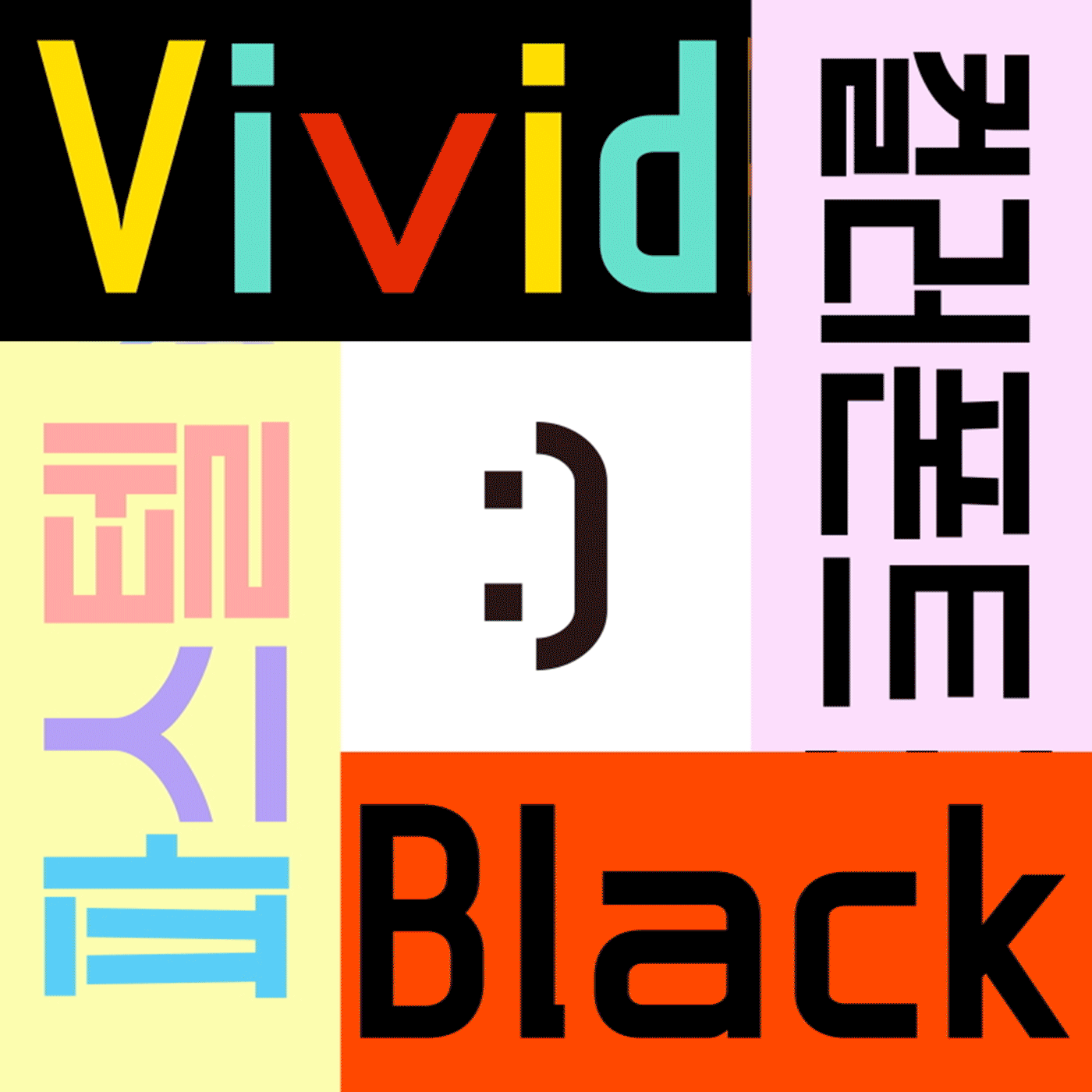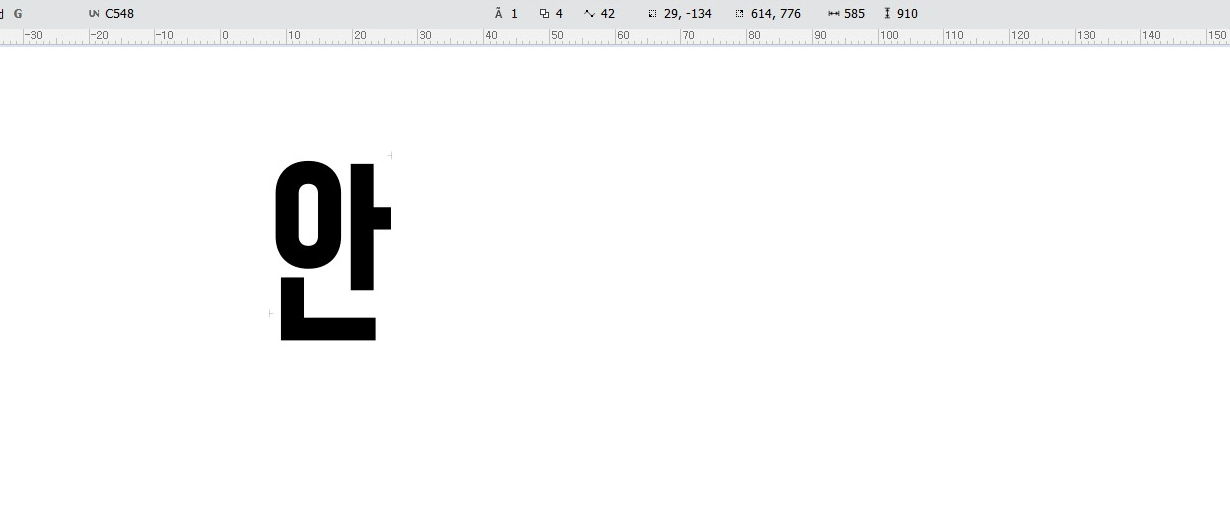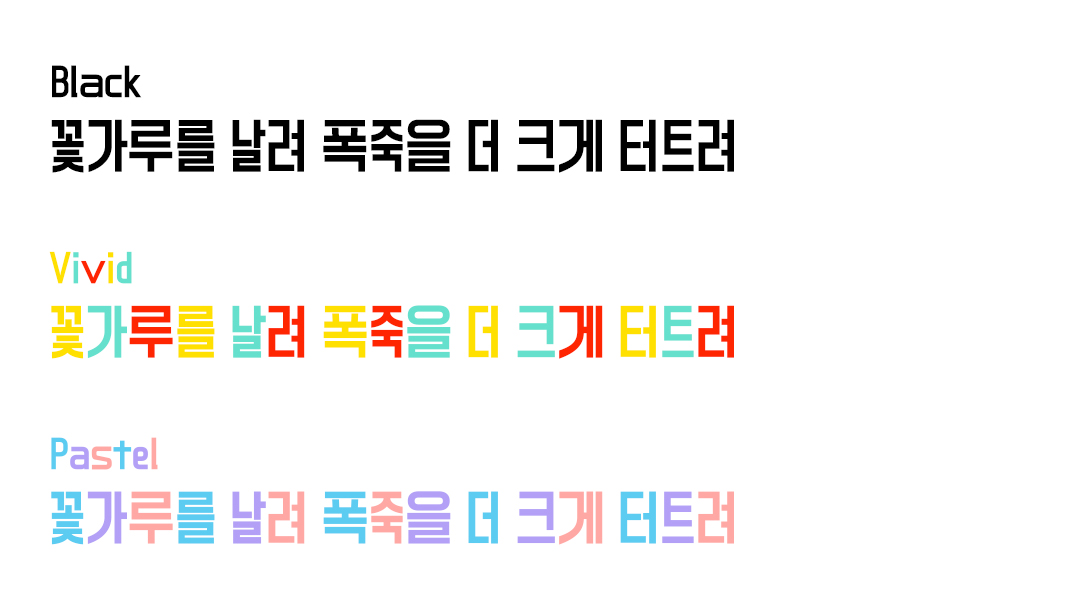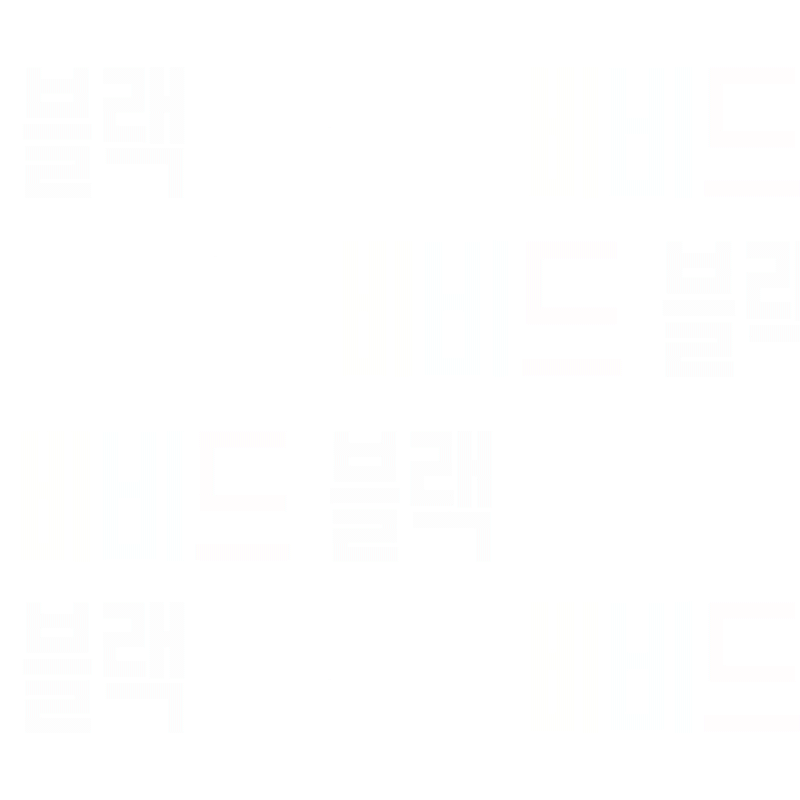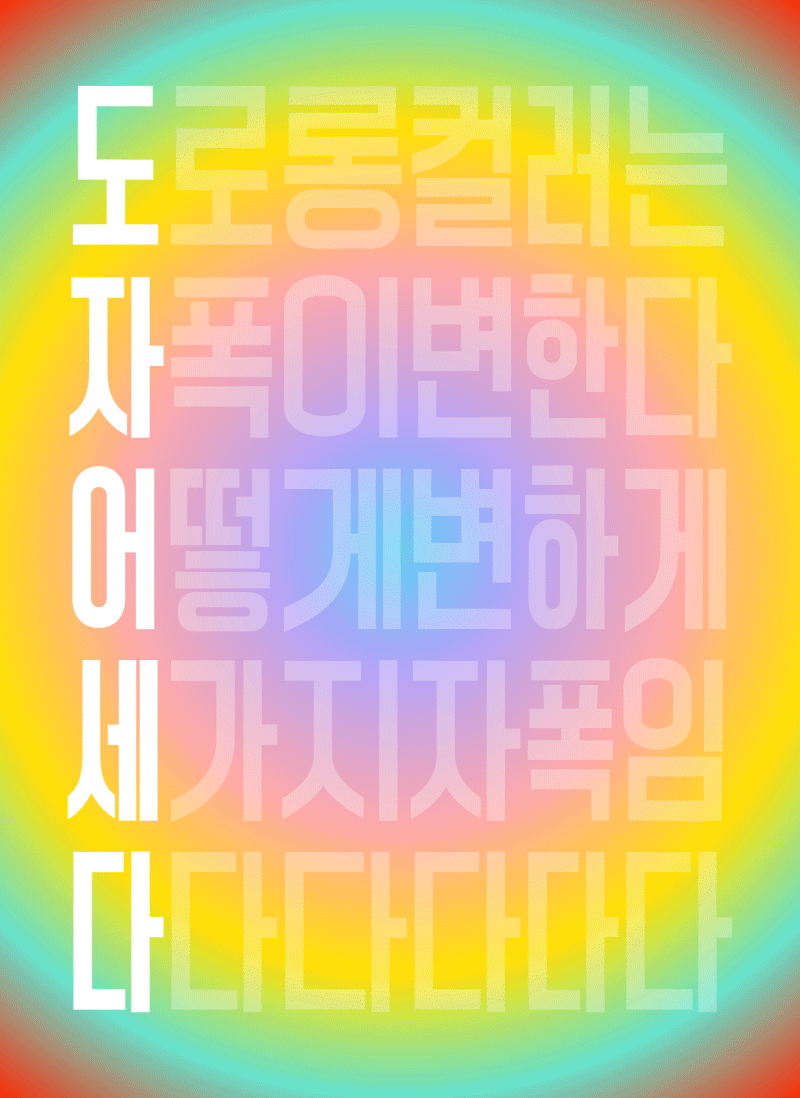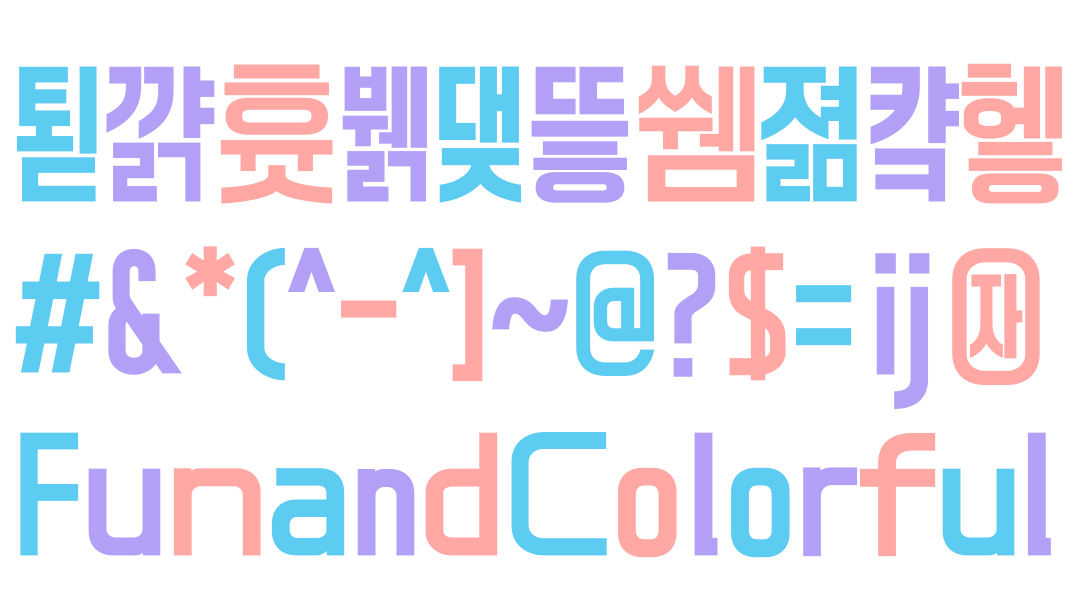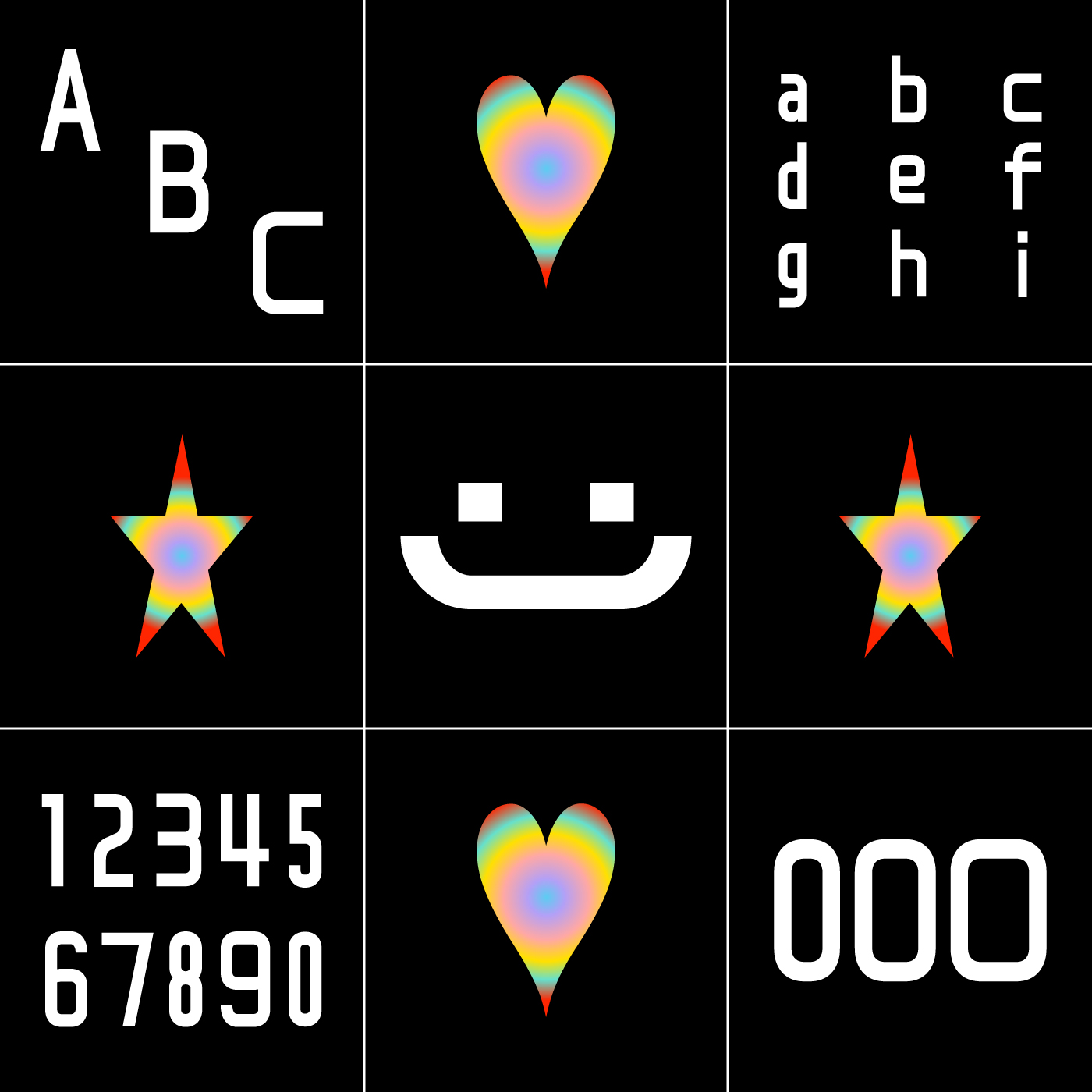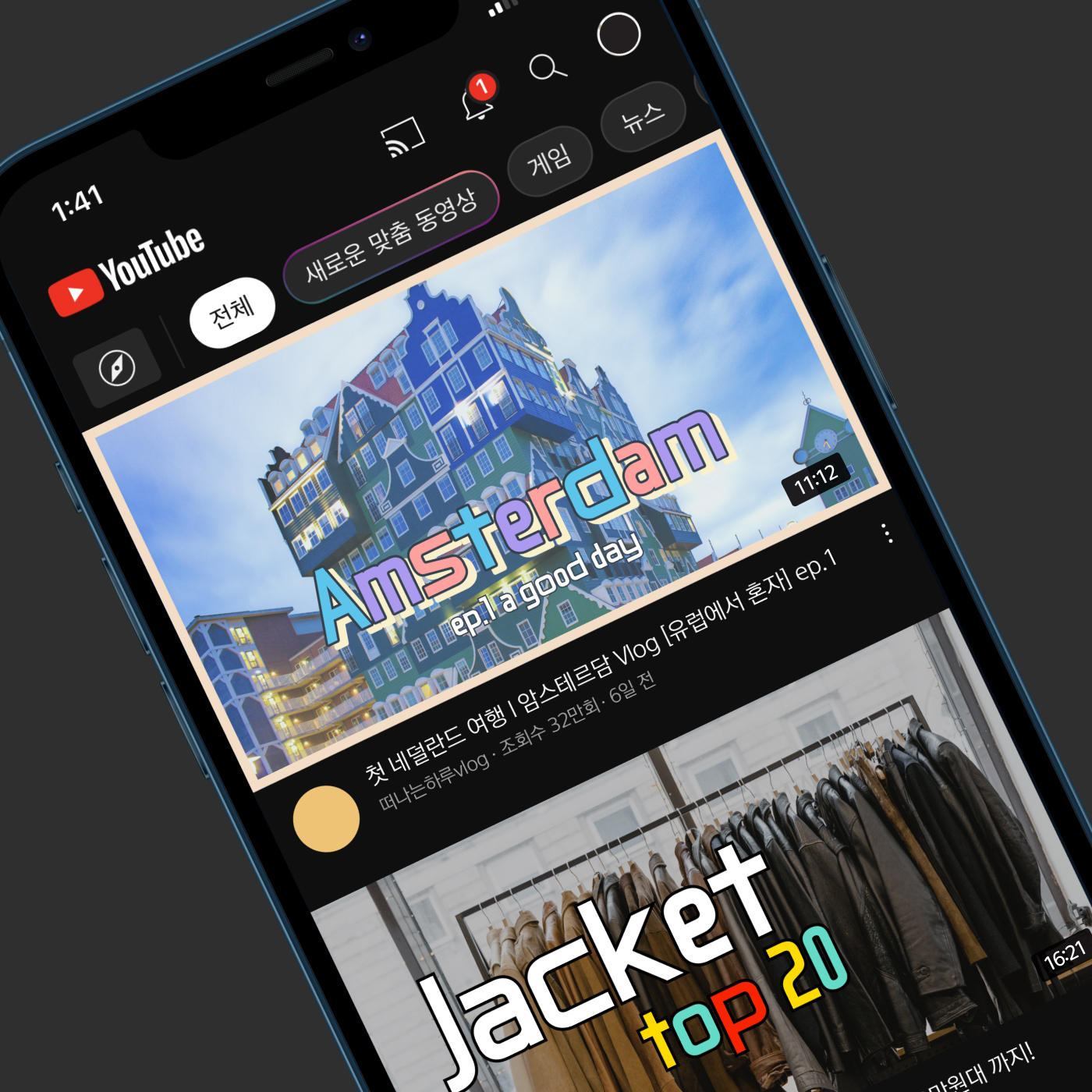
안녕하세요. 2023년의 2번째 신서체, 더욱 다채롭고 재미있는 폰트생활을 도와줄 2월의 신규 폰트 「Rix도로롱-Color」를 소개합니다! Rix도로롱컬러는 도로롱 시리즈의 New 서체로 컨셉에 따라 활용하기 좋은 Black, Vivid, Pastel 3가지 컬러 조합이 포함되어 있는 컬러폰트입니다. 이번 폰트 제작을 담당한 이수하 디자이너와의 인터뷰로 자세한 이야기 들어봤습니다 :)
도로롱 시리즈의 벌써 다섯 번째 폰트, Rix도로롱컬러 제작을 맡으셨는데 어떻게 작업하셨는지 궁금해요.
일단 도로롱 시리즈가 배리어블 폰트로 제작이 잘 되어 있어서 편하게 기획과 제작까지 할 수 있었습니다. (현주 디자이너님 감사합니당 😊) 저희 폰트릭스 서체 중 대체글립을 활용한 재미있는 폰트들이 많은데요. 저는 도로롱에도 접목시켜 보면 어떨까 생각하다 기획을 하게 되었고, 색상도 고민 없이 편하게 사용하실 수 있도록 *컬러폰트로 제작했습니다.
*컬러폰트
사용자가 따로 입력하지 않아도 비트맵이나 벡터로 폰트에 다양한 색이나 질감 등이 적용된 채 화면에 출력되는 폰트
주요 특징 및 주목할 점이라면?
Rix도로롱컬러는 대체글립을 활용하여 순서대로 자폭이 커졌다 작아졌다 하는 재밌는 요소를 가지고 있습니다. 유튜브에 주로 쓰이는 타이틀 컬러들을 분석하고 조합해 만들어낸 ✨비비드, 파스텔✨ 폰트까지 다채롭게 사용하실 수 있습니다!
디자이너가 생각하는 Rix도로롱컬러의 쓰임은?
처음에 기획했던 대로 썸네일이나 홍보물 타이틀 등 컬러 고민 없이 편하게 제목용으로 사용해 주시면 좋을 것 같습니다.
다채로운 폰트생활
Rix도로롱컬러는 3가지 컬러 조합으로 구성된 컬러폰트입니다. 폰트 파일 자체에 지정된 컬러 그래픽이 포함되어 있기 때문에 추가 작업 없이 간단하게 다채로운 표현이 가능합니다.
재미있는 폰트생활
Rix도로롱컬러는 순차적으로 자폭이 변하는 특징을 갖고 있습니다.
쓰기만 하면 따로 폭을 조절하지 않아도 적용되는 효과로 쉽게 재미있는 표현이 가능합니다.
순서에 따라 다르게 나오는 글자 폭은 재밌고 풍부한 표현을 가능하게 합니다. 이를 가능하게 하는 대체글립은 Adobe 프로그램 CC 이상에서만 사용 가능합니다.
대체 글립으로 한글 2,350자 이외의 받침이 있는 글자도 표현할 수 있으며, 동일한 특징이 적용된 영문, 숫자, 여러 특수 기호들도 조화롭게 사용할 수 있습니다.
이렇게 활용해 보세요🪄
제목용으로 활용하기 적당한 굵기로 포인트가 되는 영상 타이틀로 사용하기 좋습니다. 중간 텍스트나 자막용으로 쓰기에도 좋아서 다양한 활용도가 기대됩니다.